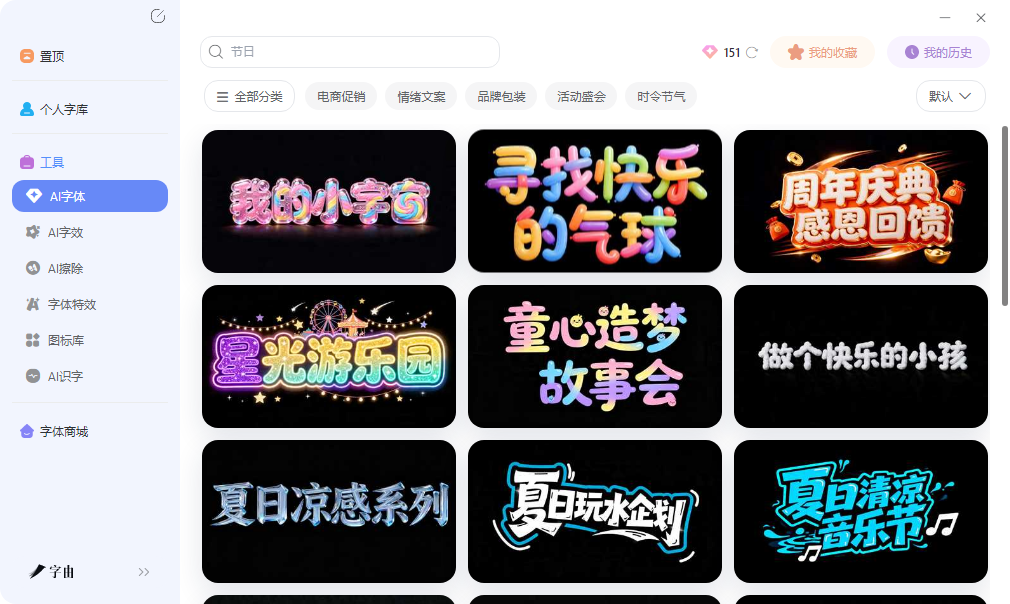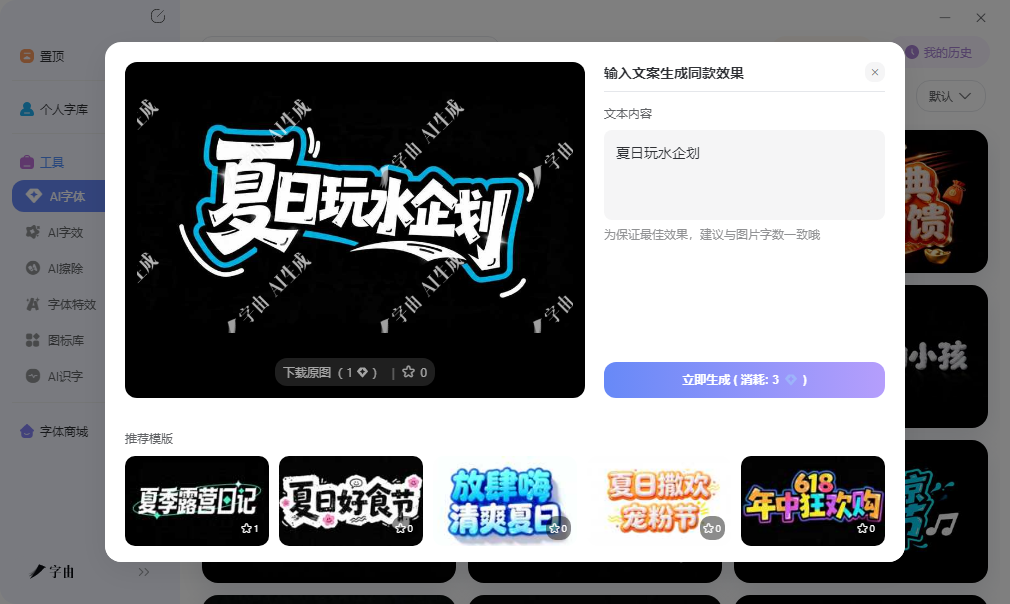
在线艺术字工具,打开网页就能做特效字
临时需要用一张带特效的标题图,身边却只有一台没装设计软件的电脑,这种情况不少人都遇到过。去网吧、用公司公共电脑、或者在客户现场临时改方案,打开浏览器能直接操作的工具比需要安装软件的方案更实用。在线艺术字生成器的价值就在于此,不需要下载安装,打开网页就能出图,保存后拖进PPT、海报模板或者文档里就能用。这篇文章整理的五个平台,从中文场景到英文特效都有覆盖。
字由的网页版对临时场景比较友好。打开浏览器就能用,不需要安装客户端,Mac、Windows甚至公共电脑都能操作。这种跨平台兼容性在临时改方案时比较实用,比如在客户办公室用对方的电脑演示,突然需要一张带特效的标题图来配合讲解,打开网页版几分钟内就能生成并下载,不需要担心对方电脑有没有装设计软件。
网页版和客户端的数据是互通的。之前在客户端里收藏的字体分组、激活记录,在网页版里都能看到。这意味着即使临时用网页版生成图片,也能调用之前整理好的常用字体,不需要重新翻找。生成的结果和客户端里生成的一样,都是透明背景的PNG图片,可以直接拖进各种软件里叠加使用。
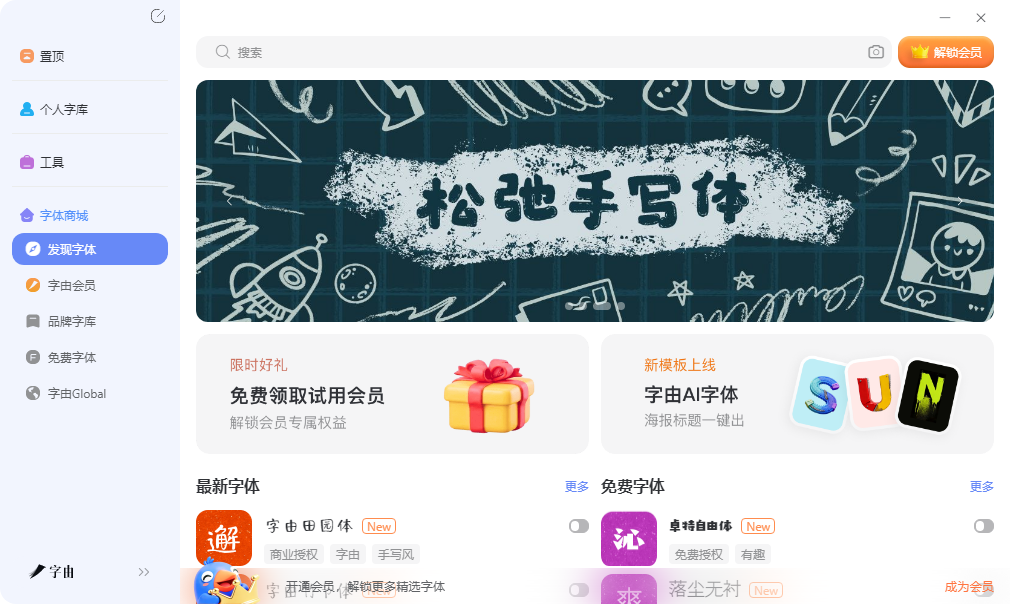
风格方向上,网页版的AI字体覆盖了国潮、科技、霓虹、节日、手写等多种类型。做春节活动海报就选红色喜庆模板,做科技产品发布就选冷色调发光效果,做文创品牌就选手写质感类。左侧的风格标签可以快速定位,不需要在海量模板里漫无目的地翻。确定风格后输入自己的文案,系统自动渲染成带特效的图片,整个过程不需要接触任何专业设计概念,比如图层样式、混合模式、蒙版这些,对没有设计基础的人来说门槛比较低。
网页版还集成了AI字效功能。如果已经在字体库里激活了某款字体,想给它叠加一些额外效果,比如发光、投影或者渐变,可以直接在网页版里操作。基础面板调节字号和粗细,进阶面板调整配色和效果强度,个性化空间比较足。这个工具和字体库是打通的,先选字体再加特效,几分钟内就能拿到成品。免费用户每日有算力额度,登录赠送的点数足够应付日常轻量使用,临时做几张配图完全够用。
生成后的图片可以直接复制粘贴到聊天窗口或者邮件里发给同事确认,也可以保存到本地再拖进设计稿。对于需要快速出概念图、和客户确认方向后再做精稿的场景,这种即拿即用的方式效率比较高。
2、LetterGenerator
LetterGenerator是一个艺术字母生成器,专注单个字母的艺术化处理。用户输入一个字母,系统会生成多种艺术风格,包括涂鸦、泡泡字、立体字等。这个工具对需要做首字母装饰、Logo设计或者字母海报的用户比较实用。
和生成整段文字的工具不同,LetterGenerator专注单个字符的艺术化,效果比较精细。作为在线艺术字的补充渠道,它的优势在于针对性强,适合需要突出某个字母的场景,比如品牌首字母、名字缩写等。生成的结果可以下载为图片,也可以复制为文本格式,使用场景比较灵活。
3、FontGenerator.art
FontGenerator.art是一个艺术字体生成器,界面比较简洁。输入文字后,系统会转换为多种美化字体样式,包括花体、粗体、手写体等装饰性变体。这些变体基于Unicode字符集,可以直接复制粘贴到社交媒体、聊天软件或者文档中使用。
和产出图片的工具不同,FontGenerator.art生成的是文本字符,可以在任何支持Unicode的平台上显示,后续需要修改文字内容时直接编辑即可,不需要重新生成。作为在线艺术字的渠道,它的优势在于灵活性高,适合社交媒体直接使用。网站上还提供了多种预设风格,点击即可切换,不需要手动调参数。生成的特殊字符在Instagram、Twitter、Facebook等平台上都能正常显示,适合用来做个人简介、帖子标题或者评论区的装饰文字。
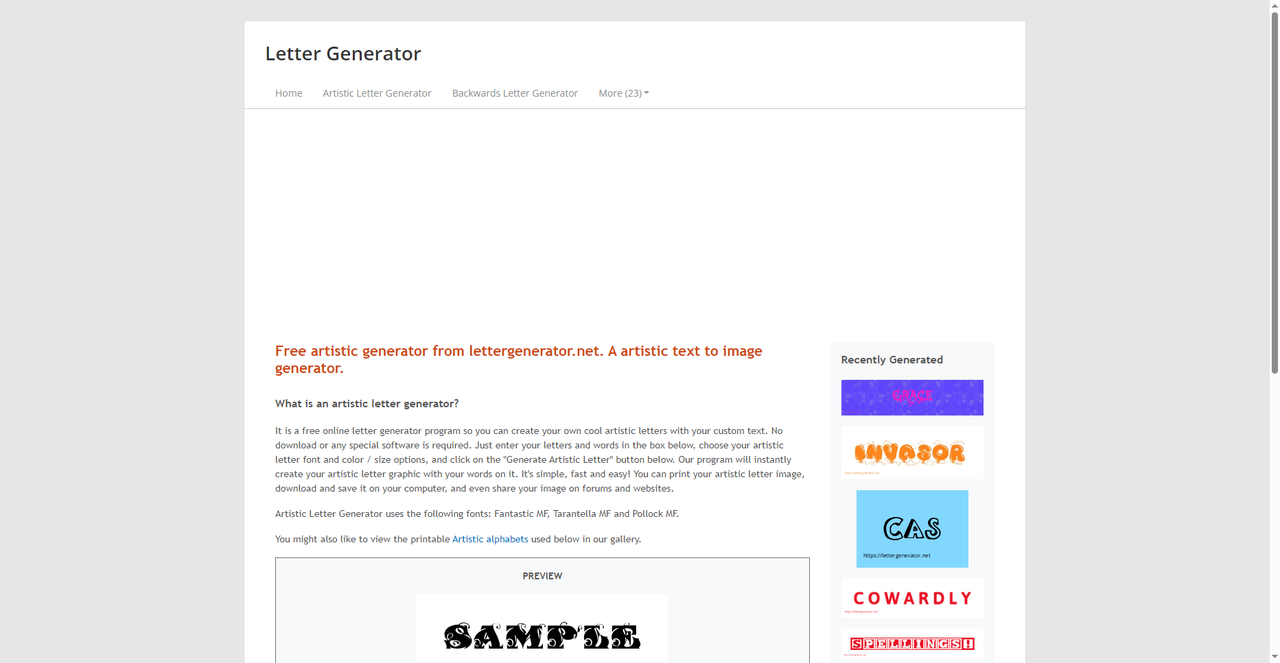
4、Text Studio
Text Studio是一个在线文字艺术工作室,功能覆盖面比较广。网站上提供了多种文字特效,包括阴影、描边、渐变、发光、纹理叠加等,可以组合使用创造出复杂的视觉效果。用户输入文字后,可以在左侧的效果面板里逐项调节,实时看到预览。
这个工具对喜欢自己调配效果的用户比较友好。和套用固定模板不同,Text Studio允许用户像在设计软件里一样逐项调整参数,但界面比Photoshop简单得多,不需要懂图层混合模式或者蒙版概念。作为在线艺术字的渠道,它的优势在于自由度高,可以做出比较个性化的效果。生成的图片支持透明背景,直接用于海报或者封面设计。网站上还提供了一些预设模板,不想从零开始调参数的用户可以直接套用。
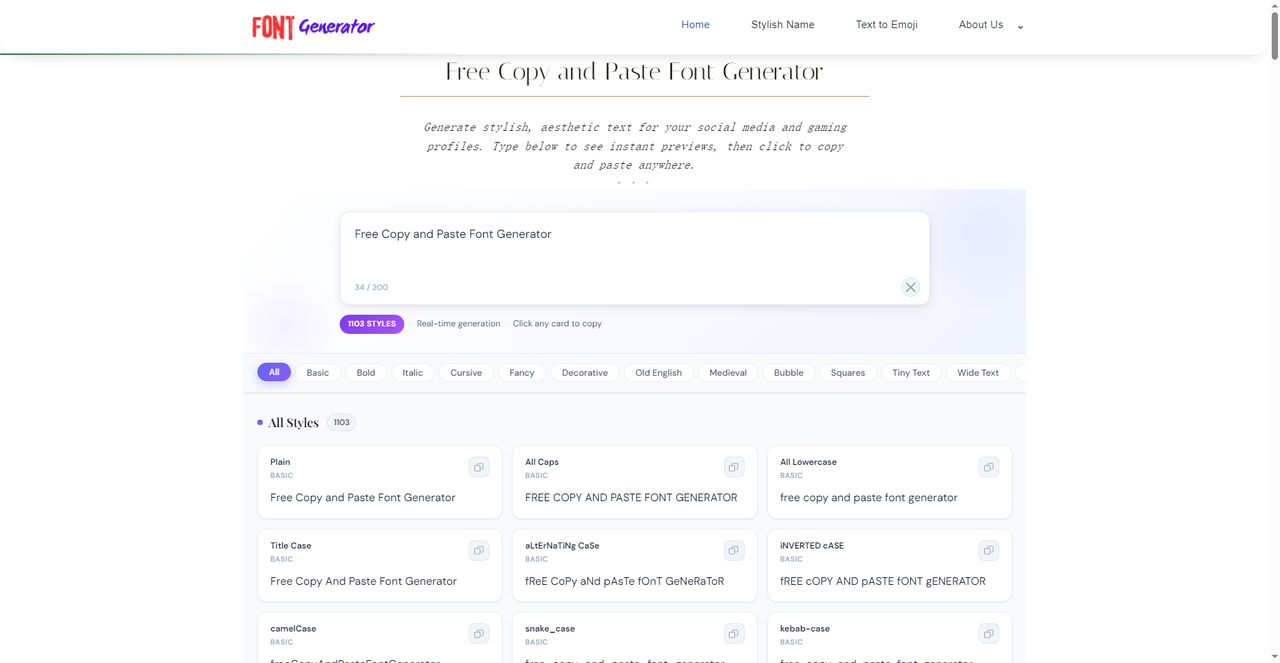
5、TextPro
TextPro是一个专注3D文字效果生成的在线工具。网站上的模板偏向立体感和质感渲染,金属、玻璃、霓虹、火焰等方向都有覆盖。用户输入文字后选择模板,系统自动应用对应的3D渲染效果,生成一张带立体感的标题图片。
这个工具对需要做视觉冲击力强海报的用户比较友好。3D效果在常规字体库里很难找到,即使找到了字体文件,也需要在C4D或者Blender里建模渲染才能实现,门槛很高。TextPro把这种复杂效果简化为几次点击,不需要任何3D软件基础。作为在线艺术字的渠道,它的优势在于效果层次丰富,适合做活动海报、游戏宣传图或者电商大促标题。生成的图片可以直接下载使用,部分高级效果需要付费,但免费版本的基础3D效果对一般海报场景已经够用。
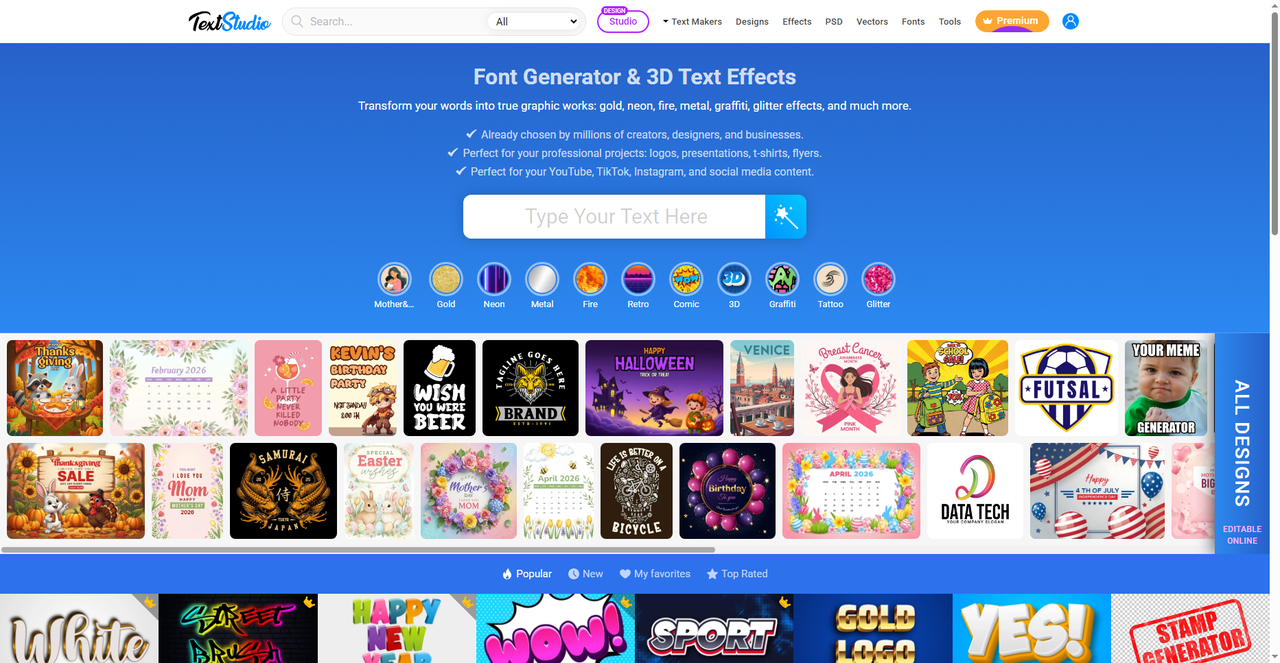
字由的网页版在跨平台兼容性和中文场景覆盖方面表现不错,配合每日免费额度,作为在线艺术字的主力渠道比较省心。TextPro的3D效果层次丰富,适合需要视觉冲击力的项目。Text Studio的自由度高,适合喜欢自己调配效果的用户。FontGenerator.art产出可编辑字符,适合社交媒体直接使用。LetterGenerator则专注单个字母的艺术化,适合Logo和首字母场景。